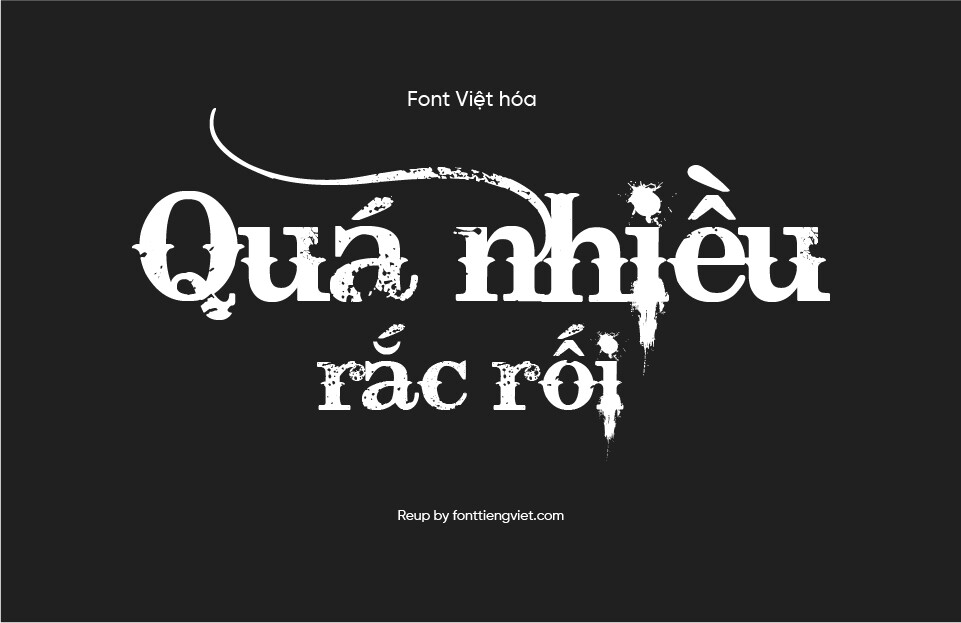
Font Việt hóa UVF Bleeding Cowboys
Giới thiệu về Font Việt hóa UVF Bleeding Cowboys
Nếu bạn đang tìm kiếm một phong cách thiết kế vừa mang hơi hướng cổ điển, vừa đầy sự phá cách thì Font Việt hóa UVF Bleeding Cowboys chính là sự lựa chọn hoàn hảo nhất. Đây là một bộ Font Miễn Phí nổi tiếng trong cộng đồng thiết kế nhờ những đường nét uốn lượn mang đậm chất nghệ thuật Grunge. Với sự kết hợp độc đáo giữa các nét thanh mảnh và những chi tiết “chảy” tự nhiên, bộ font này mang đến một cảm giác hoang dã của miền Tây nước Mỹ nhưng vẫn đảm bảo tính thẩm mỹ cao khi ứng dụng vào các văn bản tiếng Việt nhờ bảng mã đầy đủ dấu.
Đặc điểm nổi bật của Font Việt hóa UVF Bleeding Cowboys
Phong cách thiết kế Grunge độc đáo
Đặc trưng lớn nhất của Font Việt hóa UVF Bleeding Cowboys là sự kết hợp giữa chữ viết tay nghệ thuật và phong cách bụi bặm. Các chữ cái có phần chân kéo dài, được trang trí bằng những họa tiết hoa văn tinh xảo, giúp tiêu đề của bạn trở nên nổi bật và thu hút ánh nhìn ngay lập tức. Đây là công cụ đắc lực cho các bạn học sinh làm báo tường hay bìa sách.
Tính ứng dụng linh hoạt trong sáng tạo
Dù có vẻ ngoài khá cầu kỳ, nhưng Font Việt hóa UVF Bleeding Cowboys lại rất dễ phối hợp trong các thiết kế poster phim, bìa album nhạc hoặc thiệp mời sự kiện. Việc sử dụng font chữ này giúp truyền tải thông điệp về sự cá tính, mạnh mẽ và một chút bí ẩn. Bạn có thể dễ dàng cài đặt font trên các phần mềm thiết kế phổ biến hiện nay.
Kết luận và cách sử dụng hiệu quả